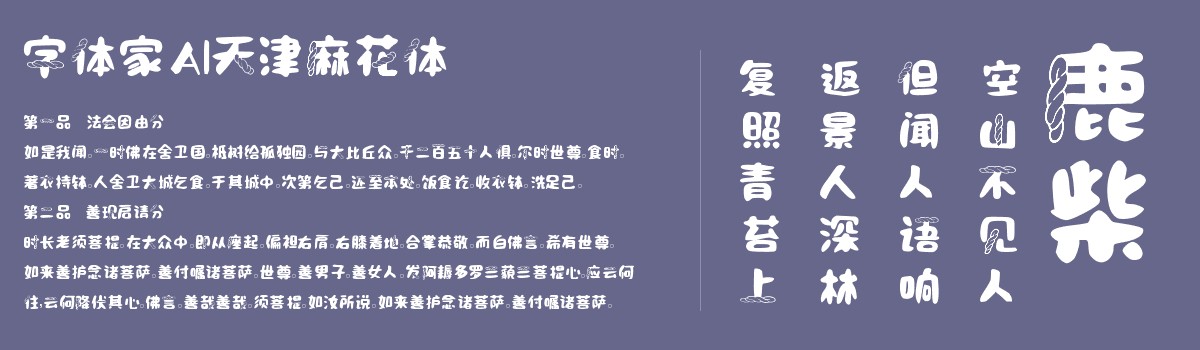
字体家AI天津麻花体
字体家AI天津麻花体这是一款由字体家AI神笔造字生成的艺术字体,其创意灵感来自美味的天津麻花,通过将部分笔画变成卡通麻花形态,文字一下子就生动了起来。
这种字体不仅为简单的文字增添了新鲜感,还让任何广告或文案都充满了趣味和吸引力。无论你是做广告设计,还是在为文案寻找亮点,天津麻花体都能帮助你的作品瞬间活过来,吸引读者的目光。
而且,随着AI技术的发展,像这样独特的字体越来越多样化,创造了更多的视觉表现可能性。总之,对于想要增添创意的作品来说,这款字体绝对是一个有趣又有效的选择!